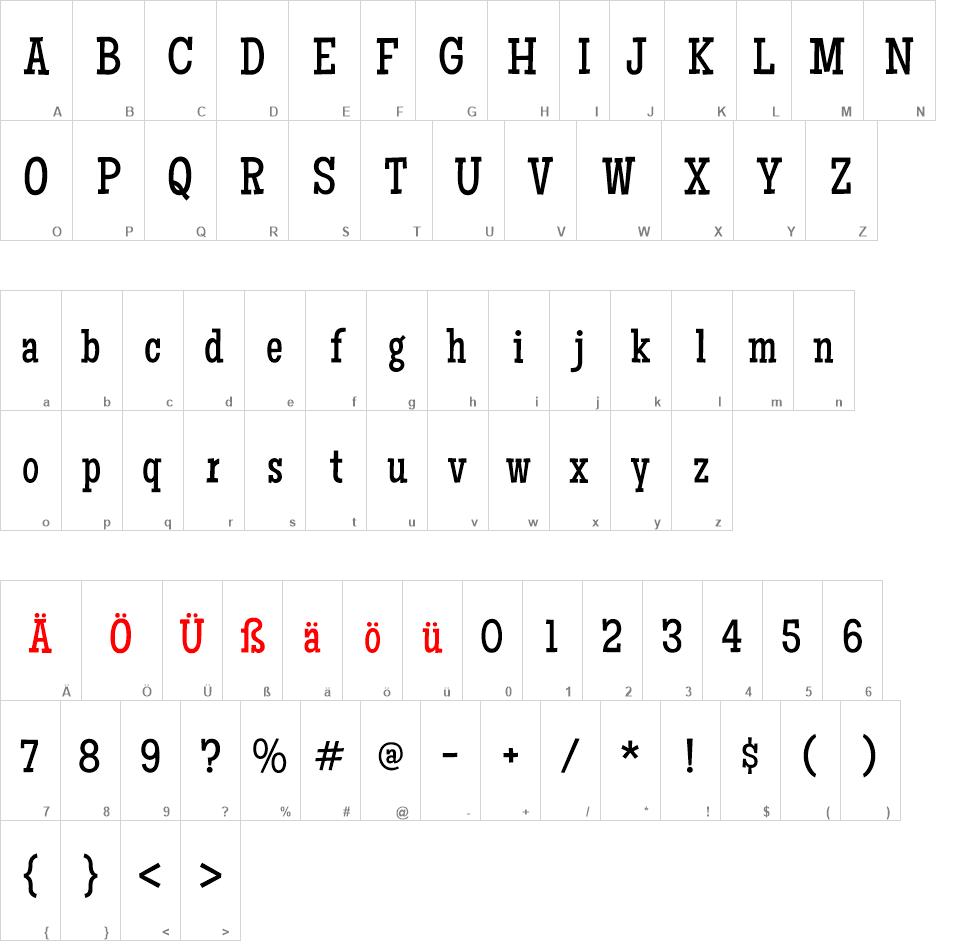
Maiden Orange Font
Maiden Orange ist eine leichte und festliche Serifenschrift, die von den Manuskripten der 1950er Jahre inspiriert wurde. Obwohl sauber und lesbar, gleichzeitig ungewöhnlich und freundlich, hat diese Schrift auch eine breite Palette von Anwendungen. Von Kindergeschichten zur Inspiration, nehmen Sie Maiden Orange für eine Rückkehr.